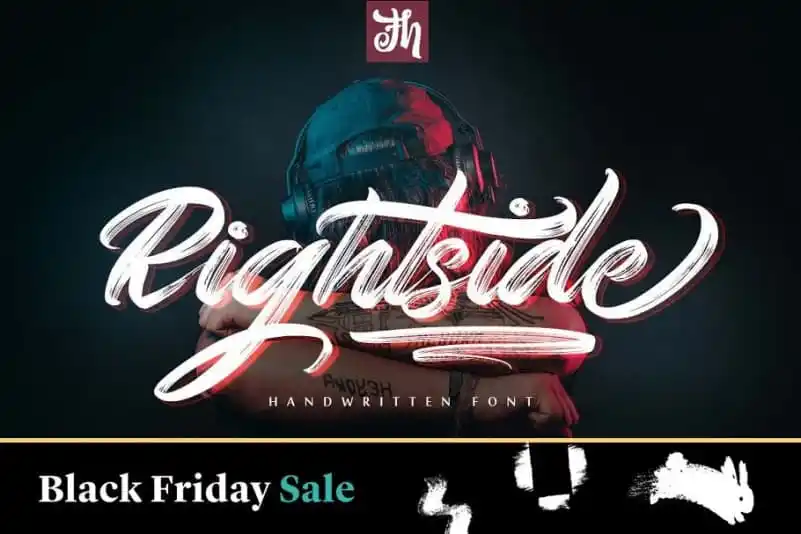
Rightside Brush Font – Download Grátis
A Rightside Brush Font é uma opção versátil para designers que procuram adicionar um toque moderno a seus projetos visuais. Seu estilo de traço feito à mão com rachadura de tinta realça o lado criativo dos elementos de design, e sua característica OpenType torna-a ainda mais funcional. Esta fonte Script é perfeita para os mais variados usos: desde a criação de logotipos e selos até estampas exclusivas, passando por elementos do evento e materiais promocionais para casamentos. Com seu estilo único e facilidade de uso, Rightside Brush Font está certa em sua categoria de Fonts Script. Seja você um designer profissional ou iniciante, encontrará noções úteis na escolha desta fonte que encanta com sua simplicidade e beleza. Seu criador, FHFont, é conhecido por oferecer uma variedade de fontes de alta qualidade para os amantes do design. Os usuários podem contar com opções robustas e versáteis, facilitando o processo criativo sem comprometer a estética desejada. Seja você um artista em busca de novos recursos ou um profissional em busca de uma solução de projeto rápida e fácil, Rightside Brush Font está aqui para ajudar.